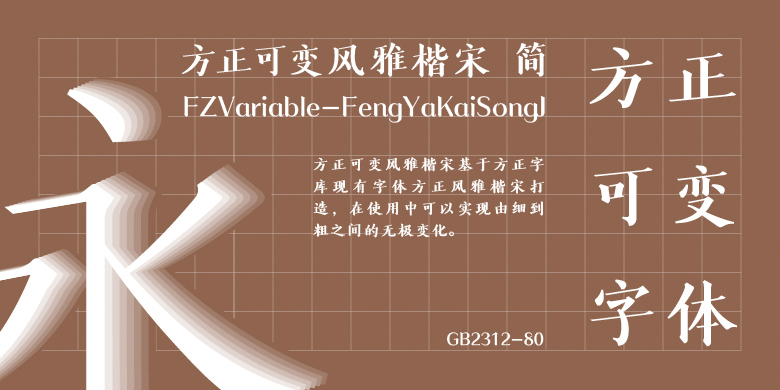
方正可變風雅楷宋字體支持文字粗細無級調節,設計師通過調整字重軸(Weight)的變化,可以實現字形的平滑連續的細微調整,滿足不同版式的設計需求。 方正風雅楷宋融合了楷體和宋體的特征,既有楷體的書寫感,又有宋體的設計感。創作者根據傳統書法的運筆法則和對當代設計的理解,試圖讓整套字體具備一定的靈動性。這款字體富有人文氣息,給人以畫般美感,是創作者深究古人書法法度所獲心得,有天質自然之美。方正風雅楷宋家族有6款不同的字重,適用于帶有清和雅致風格的標題和正文排版,粗字重的還適用于廣告、標志和產品包裝的設計。